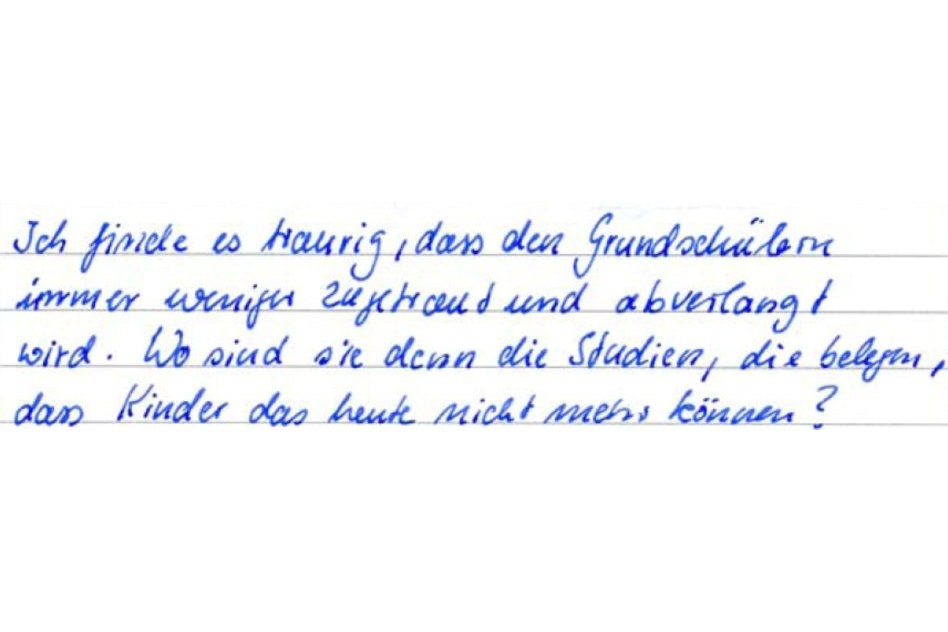
Schulreform: Schweizer wollen Schreibschrift abschaffen
Ich denke, dass wenn Kinder Formen lernen sollen, das letztens Endes bei den meisten Grundschulkinder schneller und besser geht wenn sie diese Formen auch selber machen können. Einige Kinder werden das nicht brauchen, die schaffen es rein über den Verstand. Aber so zu denken ist, so wie ich es meine verstanden zu haben, aus pädagogischer Sicht Schnee von gestern. Bei den heutigen Lernmethoden wird meistens darauf gezielt, die Lernerfahrungen so zu gestalten, dass mehrere Sinnen (gleichzeitig) angesprochen werden. Mache Schüler lernen das Rechnen in reiner Abstraktion, andere verstehen den Zahlenraum besser und schneller, wenn sie zum Zählen und addieren Bauklötze benutzen. Dadurch sollen im Gehirn die Synapsen mehrfach verknüpft werden. So können die Schüler am Ende schneller Denken und auch ‘um die Ecke’. Ein bisschen einfach gesagt vielleicht, aber ich glaube schon, dass es heute darum geht. Unsere Gesellschaft kann es sich heute nicht mehr leisten, nur die Schüler mitzunehmen die rein über das Intellekt lernen. Heute gibt es hier kaum noch Arbeit für die, die vorwiegend über das ‘tun’ lernen und weniger über das ‘denken’. Das Abschaffen der Handschrift ist demnach kontraproduktiv.
Beispiel: Wäre das Bauhaus je zu dem geworden, wenn es Fröbel und Montessori nicht gegeben hätte? Ich glaube nicht!
Es gibt viele geniale und gute Musiker, aber wären sie alle Musiker geworden, wenn der Musikunterricht in der 1. Klasse der Grundschule aus Noten lesen anstatt aus Musik machen und tanzen bestehen würde? Wohl kaum!
Das es vielen Kinder kein Spaß macht, schreiben zu lernen, liegt meiner Meinung nach nicht am schreiben selbst. Es liegt an den peniblen Schleifchenschriften mit ihren zwanghaften Verbindungen und an den Lehrern die nicht verstehen, dass es beim Schreiben lernen um das entwickeln von Formverständnis gehen soll und nicht um das peinlichst genaue kopieren von falsch verstandene Schreibmeistervorlagen aus dem 18. Jahrhundert. Die Lehrer und Behörden die jetzt das Schreiben abschaffen wollen, schmeißen das Kind mit dem Badewasser weg.
„Multisensorisches“ (?) Lernen ist sicher toll (und ich denke, dass wir außerhalb der Schule automatisch so lernen), aber zumindest angelsächsische Pädagogen würden bestimmt hinterfragen, warum das beim Erlernen der Buchstaben(formen) ausgerechnet am Schreiben dieser Buchstaben festgemacht werden soll. Die meisten englischsprachigen Kinder lernen das Alphabet nämlich lange bevor sie (feinmotorisch) in der Lage sind, Buchstaben auch zu schreiben. Das ABC sowie das Lesen einfacher Wörter ist fester Bestandteil vieler Kindergarten- und Vorschullehrpläne – gaaaaaaanz lange vor dem Schreiben. Zur Einschulung wird einfach erwartet, dass Schulanfänger das Alphabet kennen.
Þorstelinchen ist z.B. noch keine zwei Jahre alt und kann alle Buchstaben von A-Z sicher identifizieren und benennen. Wir hatten nicht die Absicht, ihr das beizubringen, aber sie hat es durch ihren Baby- und Kleinkindgebärdensprachkurs nebenbei aufgeschnappt. Es gibt zum Kurs Begleit-DVDs, die wir zum Auffrischen ab und zu in der Bibliothek ausleihen und anschauen. Im Abspann gebärdet die Lehrerin das Fingeralphabet und die lateinischen Buchstaben werden dazu eingeblendet. Das hat offensichtlich gereicht. Eine Lehrerin unserer lokalen Gehörlosenschule hat bestätigt, dass das nicht außergewöhnlich ist. Das Alphabet spielt in der Amerikanischen Gebärdensprache (ASL) eine viel größere Rolle als im (gesprochenen) Englisch. ASL-Sprecher lernen das Alphabet also oft viel eher als (Nur-)Englischsprecher. Mit Schreiben hat das nichts zu tun.
Þorstelinchen konnte übrigens gebärdete Buchstaben eher erkennen als gedruckte, obwohl ich vermute, dass nach den Kriterien, die Ralf benutzt, gedruckte lateinische Buchstaben erheblich leserlicher sein dürften als die entsprechenden Gebärden, sowohl in Bezug auf Kontrast als auch Unterscheidbarkeit verschiedener Buchstaben. :-?
Wewnn man mal davon absieht, das die Form der arabischen Ziffern (der,wirklich arabischen) tatsächlich aufgezeichnete Gebärden sind, nämlich die Handzeichen der Markthändler, die so ihre Gebote abgegeben haben. Ich habe das vor Jahren in der Grünenthal-Pharma-Hauszeitschrift "Die Waage" gelesen, die ich von meinmen Doc bekommen hatte. Leider hab ich das Heft nicht mehr, aber die Grafiken waren sehr einleuchtend.
Schrift wurde erfunden, um Sprache vom Sprecher unabhängig durch Zeit und Raum zu transportieren, nicht damit Kinder ihre Feinmotorik schulen. Worte in Stein meißeln heute nur noch Steinmetze, und keiner beklagt es. Dass Udo Beckmann, der Bundesvorsitzende des Verbands Bildung und Erziehung, sagt: „Ich halte nichts davon, das Schreiben mit der Hand abzuschaffen“, und sich in diesem Fall mit dem Grundschulverband einig ist, der sich sonst vor allem als Verfechter der Grundschrift hervortut, hat andere Gründe: Studien aus den Vereinigten Staaten und Frankreich zeigen, dass das Schreiben mit der Hand mehr ist als ein nostalgisches Relikt für Füllfederhalterliebhaber. Denn wer Buchstaben auf dem Papier erschafft, statt sie auf einer Tastatur auszuwählen, wer sie mit einer Handbewegung zu Worten verbindet, der aktiviert mehr Hirnregionen und vergisst das Notierte weniger leicht. Die relative Langsamkeit des Vorgangs unterstützt die Gedankenfindung und fordert Konzentration, nicht nur bei Kindern. Statt Achtsamkeit in Zen-Seminaren zu üben, könnte es also auch das Befolgen eines alten Bundespost-Slogans tun: Schreib mal wieder.
Im Großen und Ganzen hat er mit dem Zitat ja schon Recht – nur was hat das mit Schriftspracherwerb zu tun?
Die Schüler sind eh am Lernen und erzeugen damit schon reichlich Hirnaktivität. Erstmal sollte es doch darum gehen, zu lernen, die Sprache in grafische Zeichen umzusetzen, dabei ist das Mittel relativ egal.
Dass es nachher auch mal fürs Gehirn gut tut™, etwas mit der Hand zu schreiben ist eine ganz andere Sache. Und die (Büro-)Arbeitswelt sieht nochmal ganz anders aus ...
Und für die Feinmotorik ist dann vielleicht ja der Kunstunterricht vielleicht der bessere Platz, und für die Art des Schreibens mit der Hand, die heute noch gefragt ist. Schreiben nicht als mittel zum Zweck, um den Unterrichtsstoff zuz Papier zu bringen, sondern Schreiben, um des Schreibens willen, und damit auch den Spaß an der Schrift wecken. Was wird denn heute noch mit der Hand geschrieben? Ein Hinweisschild, ein Demo-Transparent, Graffitti an der Wand, die Anchrift auf einem Paket, oder eine Ansichtskarte aus dem Urlaub, und vielleicht ja auch mal ein romantischer Brief, statt dies lieber über SMS zu erledigen, weil die eilige Handschrift, die gebraucht wird, weil der Lehrer selbst nicht mehr die Kreide nutzt, sondern fertige Texte mit dem Beamer auf die Projektionsfläche haut, das man kaum mit kommt, und das dann die Handschrift zur Saukaue verunstaltet hat.
Handschrift lehren ja, aber besser klase statt masse.
Heutzutage werden Texte immer häufiger per Tastatur eingegeben und immer weniger mit der Hand geschrieben – soweit richtig. Daß man deshalb in der Schule die Nutzung dieses Eingabegeräts am besten im Zehnfingersystem lehrt währe sicher von Vorteil. Wenn das schreiben per Tastatur ab einer bestimmen Klassenstufe zum Standard wird, erleichtert dies möglicherweise sogar das Lernen. Technisch müßte man es noch regeln, daß die verwendeten Rechner eine vom Lehrer einstellbare Unwissenheit besitzen, denn ein Klassenarbeit mit Wikipedia, Wolfram Alpha und irgendwo im Dateisystem versteckter Spickzetteldateien wären wohl nicht sehr aussagekräftig über die Leistung des Schülers. Aber dafür gibt es auch heute schon Mittel und Wege.